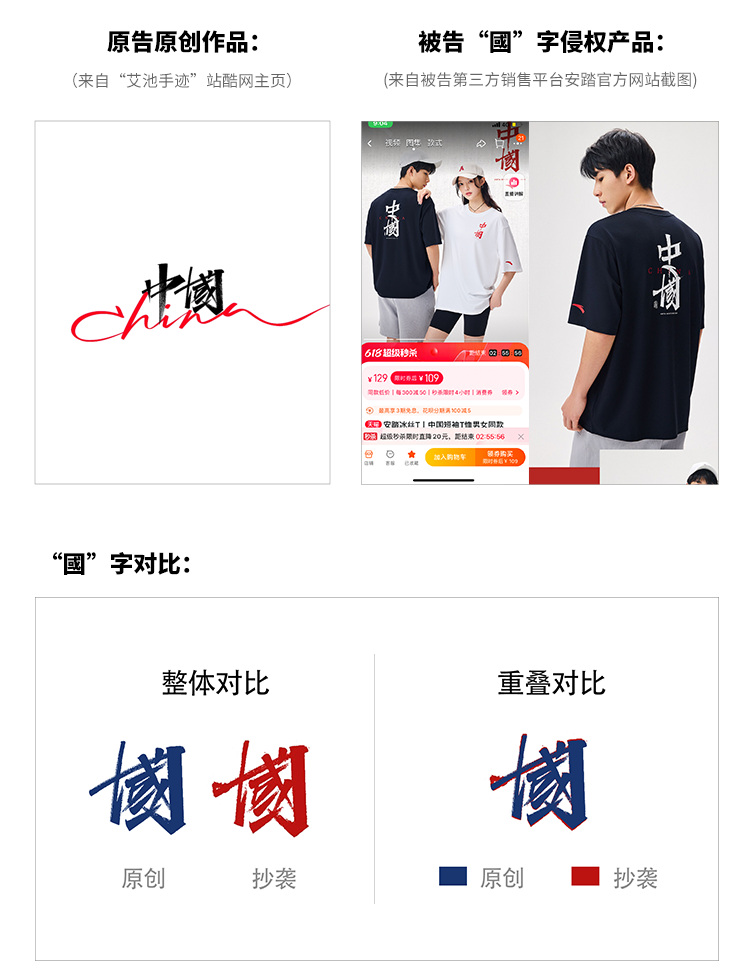
事情是这样的,2021年我创作的一组“中國”设计作品,其中作品中的“國”字,未经许可被安踏公司用在了T恤上进行大量生产和销售,通过一年左右的艰难维权,经过一审认定被告安踏公司不侵权的情况下,终于二审胜诉(改判),最终获赔经济损失及合理费用15万元。
我是一名互联网行业从业多年的视觉设计师,毕业后一直从事设计相关行业。在工作中经常为了满足客户设计需求,需要对画面字体进行设计,而我从小对书法又比较感兴趣,在这种工作模式下,商业设计+手写表现的形式,时不时会出现在我的工作中。“中國”这件作品于2021年创作完成,当时发表在了站酷等专业的设计平台,这组字是为了更好的表达“国潮汉字”,适应国潮文化崛起的市场需求下,我通过对这种文化的理解,然后借用秀丽笔、手绘板进行了大量手写尝试,然后将手写稿传到电脑中,最后通过ps调整完成的。
2023年5月一位朋友发消息给我,说安踏有款T恤上面的字,和我写的字很像。之后,我上网查询发现其T恤上“中國”二字,和我在站酷网发表过的“中國”很像,通过仔细对比发现确实如此,其中“國”字虽有改动痕迹,但是字体结构和笔画特征几乎一模一样,我意识到作品被盗用了。关于作品被盗用这件事之前有发生,也都没有维过权,主要是怕麻烦。就我了解的,当下环境下要考虑到维权,就需要投入大量时间、财力、精力来处理,所以维权比较难。但是面对这种情况又很气愤,气愤的是对方不经过我同意直接盗用我的作品在其产品上进行商用,气愤的是在如今的商业环境中,原创作品没有得到应有的尊重。
如果维权,我是个小白没有过维权经验,维权投入这么多成本不说,也不一定能得到预想的判决结果,如果不维权,以后可能还会遇到这样的侵权行为,到时怎么办,难道还要再视而不见忍气吞声吗?通过一番思考,我决定维权,不能助长这种“侵权行径”的再次发生。我先是翻看了很多维权案例,通常很多人选择了最“省事”的维权方式——自媒体声讨,这种方式基本没有结果,可能还会招来一肚子气。除非维权人是某平台大v,这件事发酵成了热点事件,涉嫌侵权的一方才会主动联系让事情尽快解决。我不喜欢与人在网上撕逼,所以后面选择了找律师代理进行法律维权。
很庆幸我找到了一家很专业的律所,在律师的帮助下,我以“安踏xx有限公司、厦门安踏xx有限公司涉嫌侵害我的原创设计作品-“中國”为由,将两家公司诉讼至了厦门市中级人民法院。
2023年9月一审开始立案,审理期间我本着能和解就和解的想法,表达了我对此案的态度,原本很自信的认为这么明显的侵权,一定能讨回公道,然而却没有想到,收到了一审败诉的判决书。我看了判决书,一审法院虽然认定了我的作品受到著作权保护,但是却认为被告的“國”字与我的“國”字不构成实质性相似,具体原因被告方搞了一百多页的证据文档,也令我“大开眼界”,所以一审维权失败。我坚持认为,被告作品中“國”字与我的“國”字二者除了起笔与第二笔有点区别外,其他部分几乎完全一样。同时我开始重新审视这个事情,反思我是不是不该维权,法律真的是公正的吗?真的是以事实为依据吗?真的和双方的经济实力无关吗?我也一度对自己是否要继续在这个行业深耕下去产生了消极的念头。但是内心的声音告诉我,我没有错,我一定要坚持维权讨回个公道!虽然一审败诉了,但是实话实说,一审法官为此案也做了好几次的调解工作,虽然最终因为双方差距较大而没有调解成功,并且最终判我败诉,但是对于一审法官对此案件所做的努力我还是表示感谢!
于是2024年4月,在律师的帮助下我配合重新整理证据资料继续上诉。将该案件诉讼至了福建省高级人民法院。我不知道这样的案件是否会改判,于是我网上了解,二审改判的几率通常非常小,大多案件在二审也是走个过程。2024年6月,在惴惴不安的心态中,我等来了二审终审判决书,压在我心头的石头也落了地,我最终得到了公平公正的判决!我的代理律师曾经和我说:要做好打到最高院的准备。我是幸运的,案子在福建省高院就得到了公正的判决!
通过此案让我对《著作权法》等法律也有了更进一步的认识,也加深了我对司法公正和法律权威性的信任。经常电视上看到“保护知识产权就是保护创新”,著作权是知识产权的一部分,我理解,对原创设计保护这件事,就如一束光,它虽然微弱却可以照亮更广阔的边缘,最终指引人们创造更多的美好生活。尝试将传统文化进行传承与创新是我的设计初心,这次经历让我也对手写字体设计有了更大的信心和方向。